タイポグラフィでは、Vox-ATypI分類によって書体を一般的なクラスに分類することができます。 1954年にマクシミリアン・ヴォックスによって考案され、1962年に国際タイポグラフィ協会(ATypI)によって採用され、1967年には英国規格として「英国規格書体分類(BS 2961:1967)」[1]として制定されました。これは、以前のVox-ATypI分類の非常に基本的な解釈と適応/修正です。
Voxは、ダウンストロークとアップストローク、セリフの形、ストロークの軸、xハイトなど、いくつかの形式的な基準に基づいて、特定の世紀(15世紀、16世紀、17世紀、18世紀、19世紀、20世紀)に典型的な主な特徴に応じて書体をグループ化する9つのタイプの分類を提案しました。[2] Vox-ATypI分類は書体の原型を定義していますが、多くの書体は複数のクラスの特徴を示すことができます。
2021年4月27日、ATypIは、このシステムの採用を取りやめたこと、そして世界中のさまざまな文字を組み込んだ新しい大規模なシステムの構築に向けたワーキンググループを設立したことを発表しました。[1]
クラシック
古典派は「ベネチアン」、「ガラルデ」、「トランジショナル」の 3 つのカテゴリに分類でき、三角形のセリフ、斜めの軸、低いストロークのコントラストが特徴です。他の分類システムでは、このグループは「オールドスタイル」または「オールド スタイル」と呼ばれることがよくあります。
ベネチアン
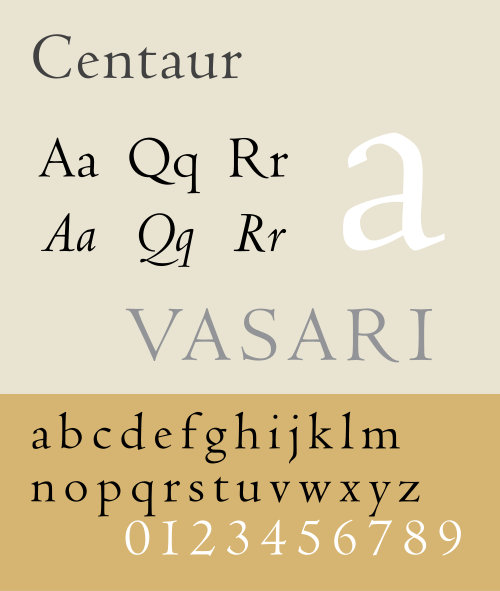
ヴェネツィア書体(ヒューマニスト、ヒューマニスティック、またはヒューマネスとも呼ばれる)には、ニコラス・ジェンソンなどのヴェネツィアの印刷業者によって15世紀に作成された最初のローマ字書体が含まれます(そのため「ヴェネツィア」という名前が付けられています)。これらの書体は、当時のヒューマニスト(ルネッサンス)写本に見られる正式な書体(ヒューマニスト小文字)を模倣しようとしました。中世のゴシックとは対照的に、これらの書体はやや丸みを帯びており、短く太い括弧付きセリフ、小文字の「e」の斜めのクロスストローク、斜めのセリフ付きアセンダ、および水平線と垂直線のコントラストが低いことが特徴です。これらの書体は、特にカール大帝が神聖ローマ帝国の統治時代に強制したカロリング小文字に触発されています。[a]
ヴェネツィア人の例としては、ケンタウロスやクロイスターなどが挙げられる。[3]
ガラルデ
アルディンとも呼ばれるこのグループは、クロード・ガラモンとアルドゥス・マヌティウスに敬意を表して名付けられました。一般的に、ガラルド体はベネチアン体よりも細かな比率で、下線と上線のコントラストが強いです。ガラルド体の太さは、斜軸に沿って分布しています。フランスでは、フランソワ1世の治世下で、ガラルド体は文法と正書法の公式な修正をサポートするツールでした。[a]
移行期
過渡期、写実主義、またはレアルは、特に啓蒙主義の合理的な精神を体現した、伝統的な時代の典型的な書体です。主線と接続線のコントラストは、最初の 2 つのグループよりもさらに顕著です。重みは、準垂直軸に従って配分されます。「過渡期」は、一方ではガラモンドの後継者を見つけ、他方ではヨーロッパのさまざまな印刷業者と品質で競争するために、新しい印刷形式を発明したいというルイ 14 世の願いの結果でした。「写実主義」という用語は、芸術運動のリアリズムとは無関係であり、スペイン国王フェリペ 2 世のためにクリストフ プランタンが鋳造した書体に由来するスペイン語の「王室」に由来しています。[4]
過渡期の書体の例としては、Baskerville、Times New Roman、その他伝統的な書体の現代的な再デザインなどが挙げられます。[3]
モダン
モダンは、ディドン、メカニカル、リニアのカテゴリーに分類でき、19 世紀後半から 20 世紀初頭の産業時代に勢いを増したシンプルで機能的な雰囲気が特徴です。
ディドン
ディドネ、つまり「モダン」な書体は、活字鋳造業者のディ・ドットとボ・ドニにちなんで名付けられました。18世紀末から19世紀初頭にかけて作られたこれらの書体は、実線と繋ぎ線(繋ぎ線は非常に細い)のコントラストが強く、文字は垂直で、括弧のない細いセリフが特徴です。これらは、ティボードー分類のディドに相当します。特にディドネによって、フランス第一帝政は、アンシャン・レジームの王たちが使用した書体とはまったく異なる書体を採用することができました。
ディドネスの例としては、ボドニやワルバウムなどが挙げられる。[3]
機械的
メカニカル、スラブセリフ、メカネスとも呼ばれるこのグループの名前は、19世紀初頭の産業革命と一致するこれらの書体の機械的な側面を想起させます。これらの書体の主な特徴は、非常に低いコントラストと長方形のスラブセリフです。これらは、ティボードーの分類であるエジプシャンに相当します。このカテゴリには、括弧付きセリフ(「クラレンドン」または「イオニック」)の書体と、角張ったセリフまたは括弧なしのセリフ(エジプシャン)の書体の両方が含まれます。[5]
機械書体の例としては、クラレンドン、エジプシャン、イオニアNo.5、ロックウェルなどがある。[3]
直系
リネアル、またはリネアルは、セリフのないすべての書体(「サンセリフ」、「ゴシック」、またはグロテスクと呼ばれる)を組み合わせたもので、すべてティボードー分類のアンティークに相当します。1967 年の英国規格では、このカテゴリを拡張して、グループをグロテスク、ネオグロテスク、幾何学、およびヒューマニストの 4 つのサブカテゴリに分割しました。
グロテスク
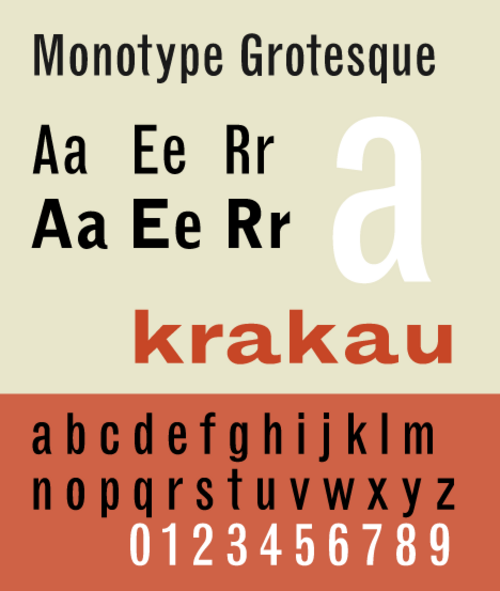
グロテスク書体は19世紀に生まれたサンセリフ書体です。太い線と細い線の間にはある程度のコントラストがあります。曲線の端は通常水平で、この書体には拍車がかかった⟨G⟩とカールした脚を持つ⟨R⟩がよく見られます。 [6]
モノタイプ社によると、「グロテスク」という用語は、その単純な幾何学的外観から「洞窟に属する」という意味のイタリア語grottescoに由来している。 [7]この用語は、当時標準であったより装飾的なモダンセリフ体やローマン体との不利な比較から生まれた。[8]
グロテスクな線状書体の例としては、Headline、Monotype 215、Grot no. 6などがある。[9]
ネオグロテスク
ネオグロテスク書体は、初期のグロテスク書体から派生したものですが、一般的にはストロークのコントラストが少なく、より規則的なデザインになっています。グロテスクとは異なり、一般的には拍車のある⟨G⟩がなく、曲線の端は通常斜めになっています。[6]多くのネオグロテスク書体は、異なる生産手段(活版印刷、鋳造活字、写真植字、 20世紀のタイポグラフィの歴史を参照)に対応するために、幅と太さの微妙な変化が大きくなっています。[10]
ネオグロテスクな線状書体の例としては、HelveticaやUniversなどが挙げられる。[11]
幾何学的
幾何学的書体は、単純な幾何学的形状、円、または長方形から構成されるサンセリフ書体です。同じ曲線や線が文字全体で繰り返されることが多く、文字間の区別がほとんどありません。[11]
幾何学的な直線的な書体の例としては、Century GothicやFutura などがあります。
ヒューマニスト
ヒューマニスト書体は、19 世紀のグロテスクな書体から派生したものではなく、それ以前の古典的な手書きの記念碑的なローマ大文字と、カロリング朝の書体に似た形の小文字に関連しています。ここでは、ヒューマニストという用語は、サブカテゴリを作成するためにリネアルと組み合わせて使用されており、これらの書体はヒューマニスト セリフ カテゴリの書体にわずかに似ています。
ヒューマニスト直線書体の例としては、Gill SansやOptima などがあります。
書道
カリグラフィは、「グリフ」、「スクリプト」、「グラフィック」、「ブラックレター」、「ゲール語」のカテゴリに分類でき、手作りであることが特徴となっています。
グリフ
グリフィック、インシズド、インサイスは、カリグラフィーの手書き文字とは対照的に、石や金属に文字を彫り込んだり彫ったりしたような書体です。そのため、小さな三角形のセリフや先細りのダウンストロークが特徴です。グリフィック書体では通常、大文字が強調され、一部の書体には小文字が含まれていません。[11]
グリフ書体の例としては、Albertus、Copperplate Gothic、Trajanなどがあります。
スクリプト
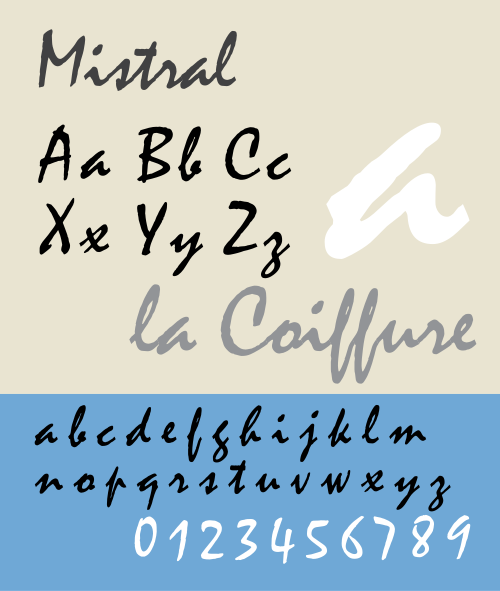
スクリプトまたはスクリプテスには、筆記体の正式な書き方を思い起こさせる書体が含まれます。羽ペンで書かれたような感じで、傾斜が強いです。文字は互いにつながっていることがよくあります。銅版画のスクリプトを模倣した書体は、このファミリーの一部です。スクリプトはイタリック体とは異なります。
スクリプト書体の例としては、Shelley、Mistral、Francescaなどがある。[3]
グラフィック
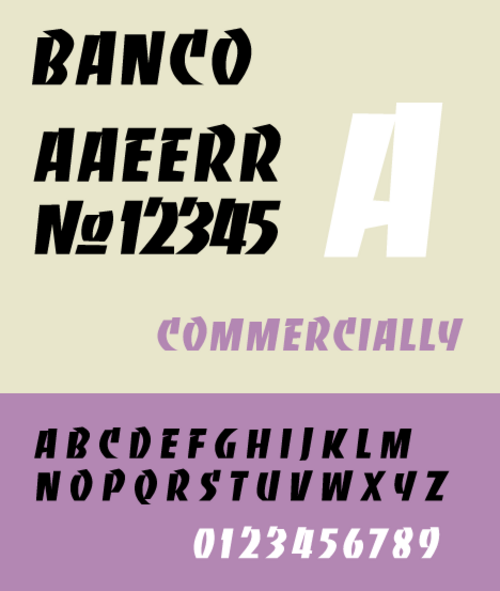
グラフィック、マニュアル、またはマニュエールは、筆、ペン、鉛筆、またはその他の筆記具でゆっくりと手書きされたオリジナルに基づいています。これらの書体は一般的に文章を表すものではなく、本文ではなく、表示や見出しの目的で使用されます。[12] Voxはもともとブラックレターとアンシャル書体をこの分類に含めていました。 [13]
グラフィック書体の例としては、BancoやKlangなどがある。[3]
ブラックレター
オリジナルの Vox 分類には、上記の 9 つのグループが含まれていました。ATypI では、さらに 2 つの分類、ブラックレターと非ラテン文字が追加されました。Voxが図に含めたブラックレター(ドイツ語: fraktur [割れた、壊れた]) は、尖った角張った形状が特徴で、中世後期の太ペンで書かれた手書き文字をモデルにしています。
ブラックレター書体ファミリーの例としては、Frakturがある。[3]
ゲール語
ゲール語のタイプは、2010年9月12日のATypIダブリン会議の年次総会で分類に追加されました。[14]
非ラテン系
この異質なファミリーは、元々の9つのVoxグループには含まれておらず、ラテンアルファベットに基づかないすべての書記体系(スタイルの区別なし)をまとめたものです:ギリシャ語、キリル文字、ヘブライ語、アラビア語、中国語、韓国語など。英国の印刷業者は伝統的にこれらを「エキゾチック」と呼んでいました。[15]
批判
キャサリン・ディクソンは 2002 年の論文で、Vox と British Standard の両方のカテゴリが、20 世紀初頭のデザイン文化に由来するディスプレイ書体よりもローマン書体を優先していることを批判しました。例として、ディクソンは、これらの分類システムでは「『ヒューマニスト』書体は『ガラルデ』書体と形式的に区別されていますが、形式的な違いは非常に微妙で、そのような区別が適切な書体はごくわずかです。しかし、多数のスラブ セリフ書体、クラレンドンまたはイオニック (括弧付きのスラブ セリフ)、エジプシャン (角張った括弧なしのスラブ セリフ) は、単に一緒にグループ化されています」と述べています。ディクソンは、ローマン体への一般的な焦点は時代遅れであると異議を唱え、「サンセリフ体やスラブセリフ体のデザインに導入されたより繊細な表現により、テキストとディスプレイの区別はますます無意味になり、テキストの目的にこのような書体が幅広く使用されるようになった」と述べています。ディクソンの結論は、これらのシステムは 1967 年以来変更されておらず、そのため多くの現代の書体ではこれらのシステムが不十分になっているというものです。[5]ミゲル・カトポディスは、ATypI フォーラムで、1962 年の Vox-AtypI 分類全体をアップロードしてより広く利用できるようにする必要があると提案しました。なぜなら、この分類図は、書体の分類方法を理解するための多くの学生にとって今でも簡単なリソースだからです。